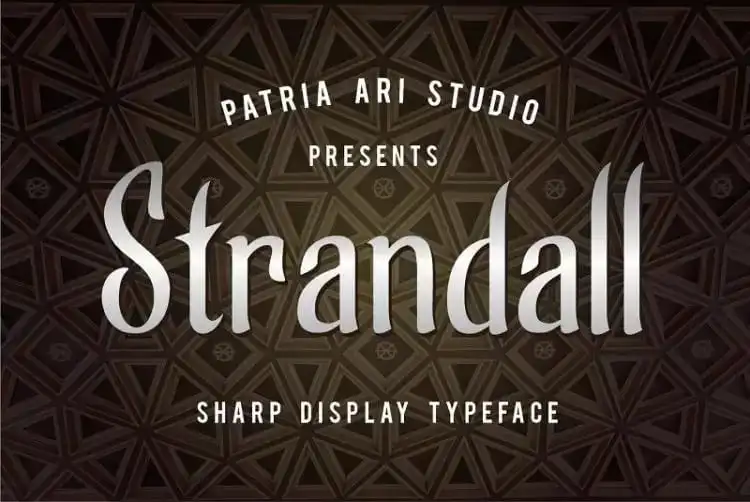
Strandall Display Font – Fonte Grátis
Strandall Display Font
Aqui está a descrição em português para a página de download da fonte ‘Strandall Display Font’: Aprenda mais sobre Strandall Display Font, uma tipografia vintage criada pela Patria Ari Typestudio inspirada nas temáticas de guerreiros. Ideal para criações que precisam de um toque retro e moderno, esta fonte vem à perfeição para projetos diversos como logotipos e marca, headlines, outdoors, sinalização, anúncios impressos, embalagens de produtos, design gráfico, etiquetas, fotografia, marcas d’água, eventos especiais ou qualquer outra aplicação que precise de um design forte e distintivo. Uma escolha inteligente para quem busca uma tipografia vintage com um toque contemporâneo, Strandall Display Font vai adicionar um ar inconfundível ao seu próximo projeto visual.